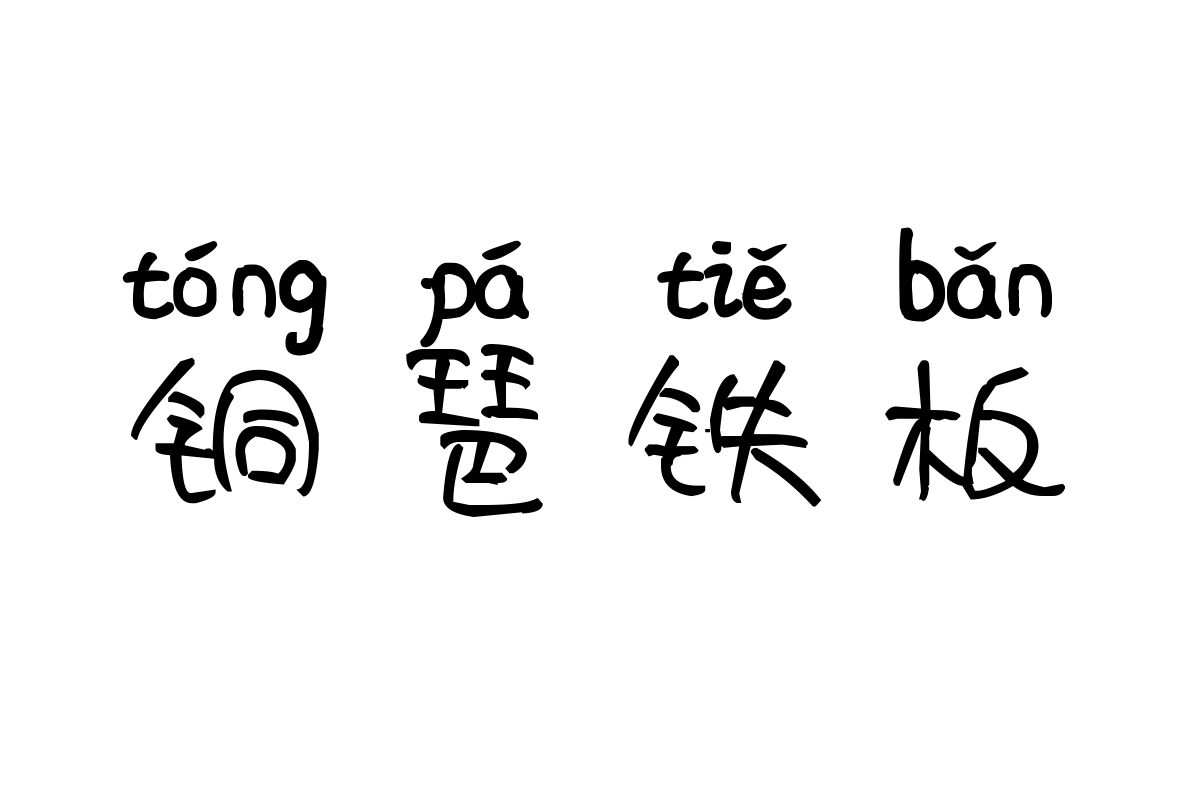
米开一世风华拼音体是一款具有独特风格的中文字体。它采用了现代的设计手法,结合了传统书法的韵味和现代审美的需求。字体线条流畅,笔触饱满有力,给人一种优雅而高贵的感觉。
这款字体的特点是字形结构紧凑,笔画粗细适中,既适合用于正式场合,也适合用于创意设计。它的每一个字都充满了生命力,仿佛在讲述着一个个故事。无论是书写还是打印,都能展现出独特的美感和个性。
此外,米开一世风华拼音体还注重细节的处理,如字间距、行间距等都经过精心设计,使得整个字体看起来更加和谐统一。同时,它还具有一定的可读性,即使在不同大小的屏幕上也能保持良好的视觉效果。
总之,米开一世风华拼音体是一款值得尝试的中文字体,它以其独特的风格和优美的外观赢得了广大用户的喜爱。